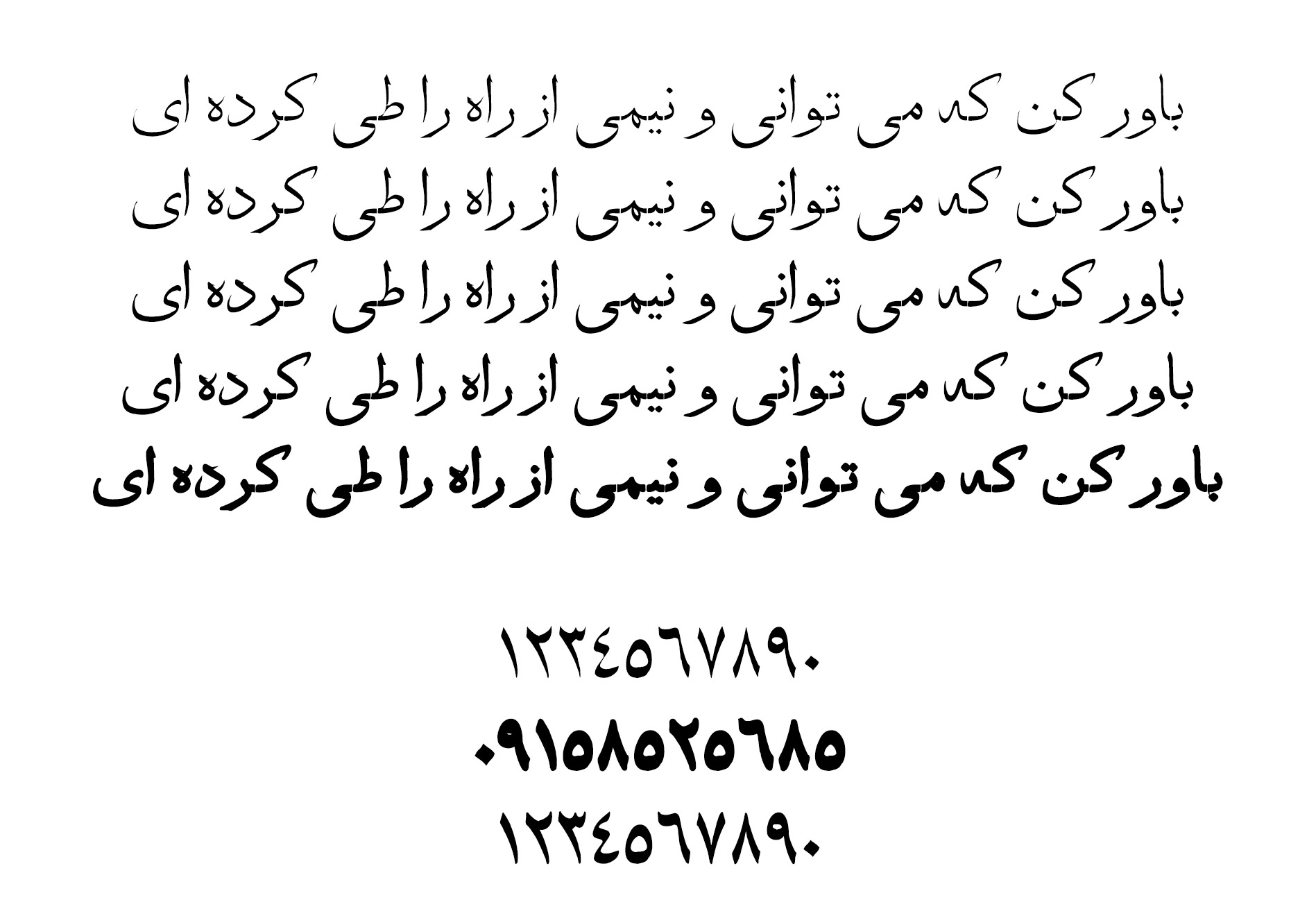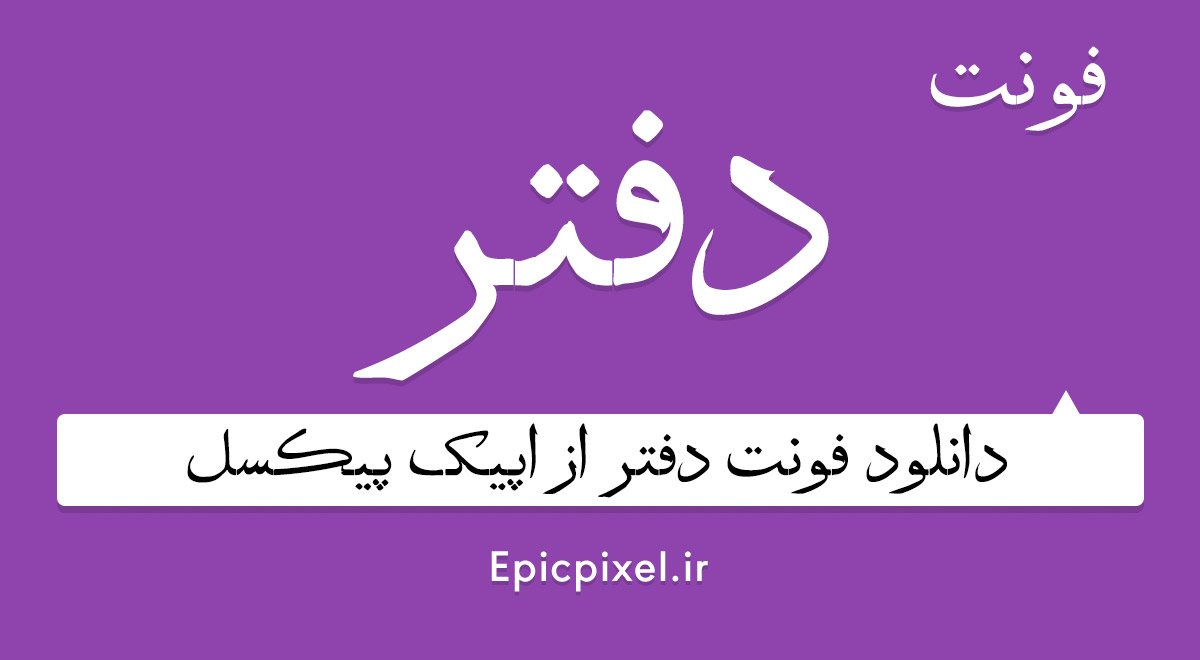
فونت دفتر، یک انتخاب هوشمندانه برای کسانی است که به دنبال ظرافت و خوانایی در نوشته های خود هستند. این فونت، با طراحی منحصر به فرد خود، در اندازه های مختلف، از ریزترین نوشته ها تا عناوین بزرگ، زیبایی و وضوح خود را حفظ می کند و به متن شما، شخصیتی خاص می بخشد.
یکی از ویژگی های برجسته فونت دفتر، وجود ترکیبات اختیاری و حروف جایگزین است که به شما امکان می دهد شکل های متنوع و جذابی را در کلمات خود ایجاد کنید و به طراحی های خود، جلوه ای نو ببخشید. این ویژگی، به ویژه برای طراحان گرافیک و صفحه آراها، بسیار کاربردی است.
همچنین، فونت دفتر، با پشتیبانی از اعراب و برخی ترکیبات خاص، به خوبی از متون عربی نیز پشتیبانی می کند و گزینه ای مناسب برای متونی است که شامل کلمات یا عبارات عربی هستند. علاوه بر این، برای استفاده در متون دوزبانه (فارسی و انگلیسی)، یک فونت انگلیسی هماهنگ با دفتر طراحی شده است که بافت و شخصیت مشابهی با فونت فارسی دارد و به یکپارچگی بصری متن کمک می کند. این ویژگی ها، فونت دفتر را به انتخابی ایده آل برای انواع کاربردها، از طراحی لوگو و پوستر گرفته تا صفحه آرایی کتاب و مجله، تبدیل کرده است.